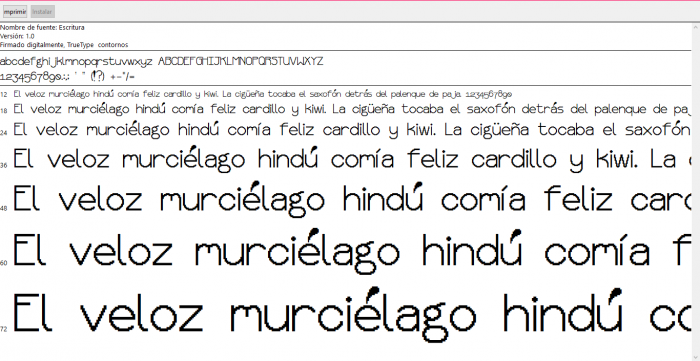
• ¡Una fuente de letra hermosa y con un estilo natural! O al menos el tipo de letra que uso para escribir en la vida real. Jajaja, qué buen chiste. En fin, espero que disfrutes mucho esta obra y no te arrepientas de haberla descargado, o por lo menos que la descargues. ¡Crea textos, diálogos o títulos con esta fuente de letra tan divertida de la que no te vas a arrepentir!
NOTA: ESTOY TRABAJANDO EN UNA ACTUALIZACIÓN DE ESTA FUENTE DE LETRA. SI LA QUIERES DESCARGAR DESPUÉS, PUEDES ESPERAR A QUE TERMINE DE MODIFICAR POR COMPLETO LA FUENTE. PRONTO ESTA FUENTE TENDRÁ UN CAMBIO RADICAL CON LA ACTUALIZACIÓN EN LA QUE TRABAJÉ, QUE CONSISTE EN MODIFICAR LAS LETRAS MAYÚSCULAS; PARA QUE, LUEGO SI QUIERES, VUELVAS A DESCARGAR ESTE ELEMENTO.
SEGUNDA ACTUALIZACIÓN: SÉ LO MÁS PACIENTE QUE PUEDAS Y ESPERA DE AQUÍ HASTA JULIO, (QUE ES CUANDO POSIBLEMENTE TERMINE). NUEVOS CARACTERES EN ESTE FUENTE DE LETRA OFRECEN CADA VEZ MÁS ACCESIBLIDAD A LA GENTE QUE ESCRIBE...  Y A LOS QUE TAL VEZ HAYAN VISTO ESTO. SE UNEN NUEVOS CARACTERES A ESTE ARCHIVO DE FUENTE DE LETRA, QUE INCLUYE: LETRAS MODIFICADAS DEL LATÍN COMPLETO (INCLUYE ACENTOS, SÍMBOLOS, COMBINACIONES, ENTRE OTROS) Y LA INCLUSIÓN DEL ALFABETO GRIEGO CON ACENTOS Y SÍMBOLOS. PRÓXIMAMENTE.